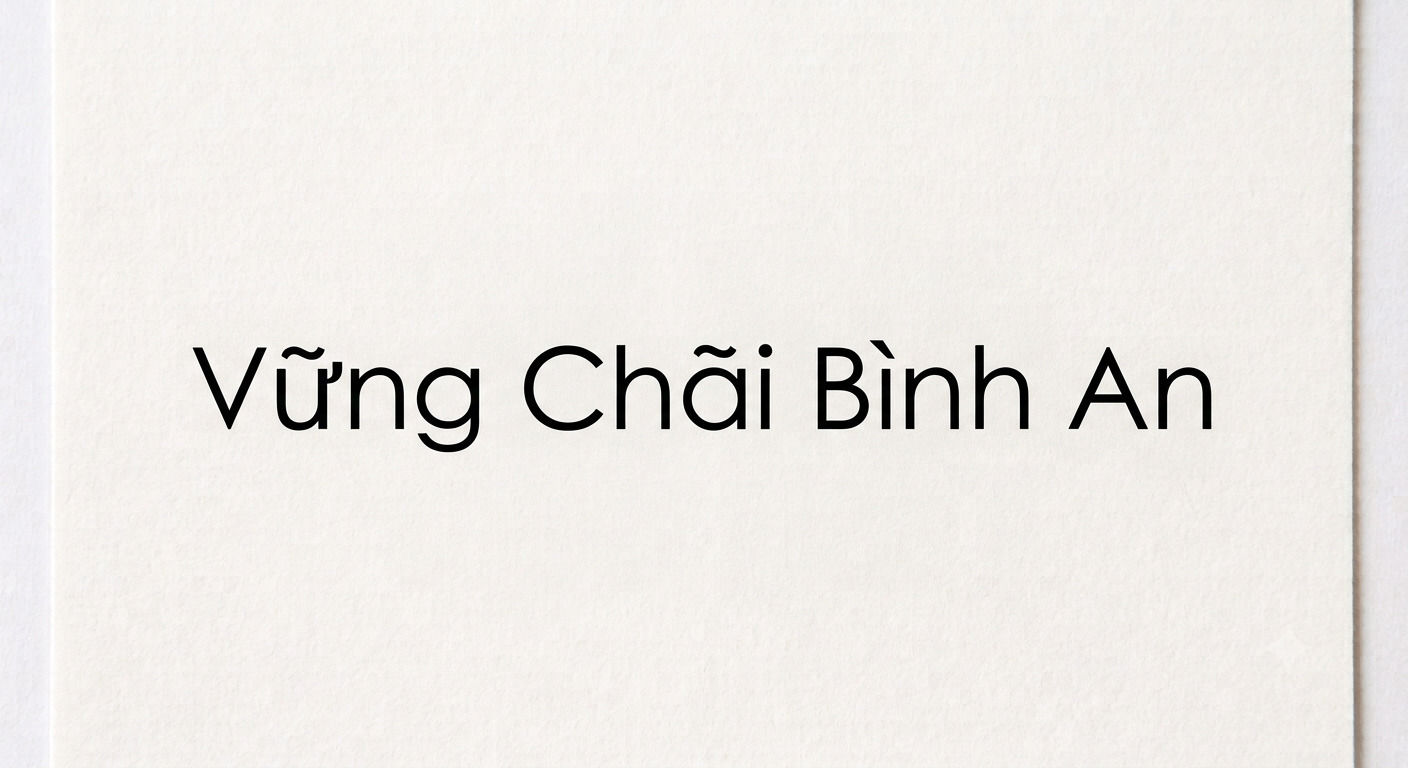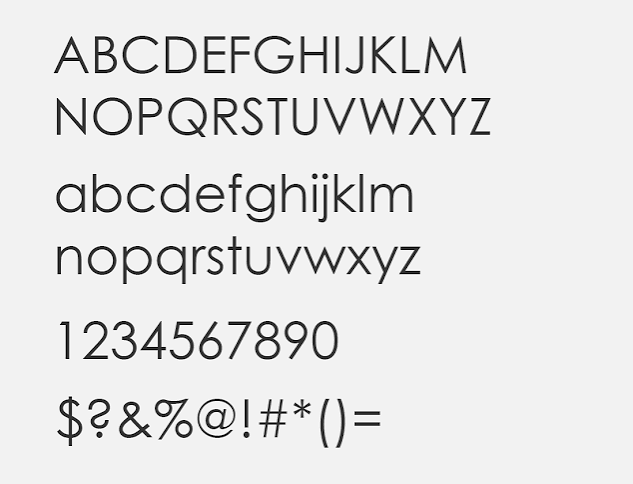
Century Gothic Font được nhiều nhà thiết kế lựa chọn nhờ kiểu chữ không chân hình học, đường nét cân đối và phong cách tối giản phù hợp với các thiết kế thương hiệu hiện đại. Tuy nhiên, một số phiên bản font trên Internet chưa được Việt hóa hoàn chỉnh, dễ xảy ra lỗi dấu, thiếu ký tự hoặc sai lệch khoảng cách chữ khi sử dụng. Điều này có thể ảnh hưởng đến độ chuyên nghiệp của logo, bao bì hoặc các sản phẩm in ấn doanh nghiệp.
Font chữ Century Gothic là gì?
Century Gothic là một phông chữ thuộc dòng Geometric Sans-serif (chữ không chân hình học) vô cùng nổi tiếng, được thiết kế bởi Monotype Imaging vào năm 1991. Lấy cảm hứng từ phông chữ Futura kinh điển và các thiết kế của Sol Hess, Century Gothic mang đặc trưng là các đường nét cân đối tuyệt đối, cấu trúc chữ tròn trịa (đặc biệt là các chữ cái ‘o’, ‘p’, ‘q’) và chiều cao ký tự (x-height) lớn. Điều này tạo nên một vẻ ngoài cực kỳ sạch sẽ, hiện đại và rất dễ đọc trên cả màn hình kỹ thuật số lẫn bản in truyền thống.
All round gothic việt hóa cũng thường được nhắc đến như một biến thể có phong cách tương đồng, mang lại cảm giác trẻ trung và tinh gọn. Tuy nhiên, Century Gothic vẫn giữ vị thế là phông chữ tiêu chuẩn nhờ độ tinh tế và sự chuyên nghiệp vượt thời gian. Bản font chữ century gothic việt hóa free được Xưởng In Viva chia sẻ đã được tinh chỉnh bảng mã Unicode chuẩn, khắc phục hoàn toàn lỗi chân chữ và dấu tiếng Việt, giúp bạn tự tin triển khai các dự án nhận diện thương hiệu quy mô lớn.
Vẻ đẹp tối giản và hình học của Century Gothic giúp nâng tầm mọi ấn phẩm quà tặng và bao bì khi phối hợp cùng công nghệ in hiện đại:
- Thiết kế bao bì thiết bị điện tử, công nghệ: Century Gothic với kiểu chữ hình học, rõ nét giúp các thông tin kỹ thuật trên hộp giấy dễ đọc, tạo cảm giác hiện đại và chuyên nghiệp.
- Thiết kế quà tặng doanh nghiệp in logo: Font Century Gothic phù hợp khi in UV trên bình giữ nhiệt, sổ tay, sạc dự phòng nhờ phong cách tối giản, giúp sản phẩm giữ được vẻ ngoài tinh tế.
- In bao bì túi giấy ngành dược phẩm: Đường nét sạch sẽ của Century Gothic giúp trình bày thông tin sản phẩm rõ ràng, tạo cảm giác tin cậy và an toàn.
- Thiết kế backdrop, banner sự kiện: Font chữ có cấu trúc cân đối, dễ nhận diện khi in kích thước lớn, phù hợp cho tiêu đề chương trình và thông điệp thương hiệu.
- Sản xuất tem nhãn decal sản phẩm: Century Gothic giúp tên thương hiệu và thông tin sản phẩm nổi bật, giữ được độ rõ nét khi in trên nhiều kích thước nhãn khác nhau.
Để font Century Gothic giữ được độ sắc nét và tính thẩm mỹ khi ứng dụng vào thiết kế bao bì, logo và các sản phẩm in ấn, designer cần chú ý các yếu tố sau:
- Chọn biến thể font phù hợp: Sử dụng Century Gothic Regular cho nội dung dài để đảm bảo khả năng đọc, trong khi Century Gothic Bold phù hợp với logo, tiêu đề hoặc thông tin cần tạo điểm nhấn trên bao bì.
- Cân chỉnh khoảng cách chữ và dòng: Century Gothic có kiểu chữ hình học với cấu trúc tròn, vì vậy cần điều chỉnh Tracking và Leading phù hợp để nội dung trên hộp giấy, túi giấy hoặc catalogue có bố cục cân đối, không bị bí chữ.
- Chuyển đổi font sang dạng vector: Trước khi gửi file sản xuất, nên thực hiện Create Outlines để tránh lỗi font và giúp đường nét chữ được giữ chính xác khi in logo, dập nổi hoặc gia công trên sản phẩm.
- Thiết lập màu in đúng chuẩn: Cần kiểm tra hệ màu CMYK trước khi in để màu chữ hiển thị đồng nhất trên các chất liệu như giấy mỹ thuật, giấy Kraft, hộp quà hoặc vật phẩm nhận diện thương hiệu.
- Kiểm tra kích thước chữ khi in: Không nên sử dụng Century Gothic với kích thước quá nhỏ trên các bề mặt thô hoặc chất liệu dễ hút mực, vì có thể làm giảm độ rõ nét của chữ sau khi thành phẩm.